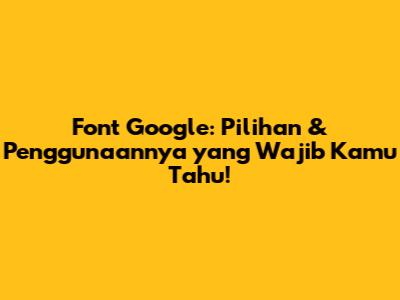
- Roboto: Roboto adalah font sans-serif yang sangat serbaguna dan mudah dibaca. Font ini sering digunakan untuk website dan aplikasi karena tampilannya yang bersih dan modern. Roboto memiliki banyak variasi gaya, sehingga cocok untuk berbagai kebutuhan desain.
- Open Sans: Open Sans adalah font sans-serif lainnya yang sangat populer. Font ini dirancang untuk tampilan di layar, sehingga sangat cocok untuk website. Open Sans juga mudah dibaca dan memiliki tampilan yang ramah.
- Lato: Lato adalah font sans-serif yang elegan dan modern. Font ini cocok untuk berbagai jenis proyek, termasuk website, logo, dan materi pemasaran. Lato memiliki bentuk yang unik dan mudah dikenali.
- Montserrat: Montserrat adalah font sans-serif yang terinspirasi oleh arsitektur kota Montserrat di Argentina. Font ini memiliki tampilan yang bersih dan geometris, sehingga cocok untuk desain yang modern dan minimalis.
- Poppins: Poppins adalah font sans-serif yang modern dan ramah. Font ini cocok untuk berbagai jenis proyek, termasuk website, aplikasi, dan materi pemasaran. Poppins memiliki bentuk yang bulat dan mudah dikenali.
- Raleway: Raleway adalah font sans-serif yang elegan dan bergaya. Font ini cocok untuk berbagai jenis proyek, termasuk website, logo, dan materi pemasaran. Raleway memiliki tampilan yang bersih dan modern.
- Pertimbangkan Tujuan Desain: Apa tujuan utama dari desain kamu? Apakah kamu ingin menciptakan tampilan yang formal, kasual, modern, atau klasik? Pilihlah font yang sesuai dengan tujuan desain kamu.
- Perhatikan Keterbacaan: Pastikan font yang kamu pilih mudah dibaca, terutama untuk teks dalam jumlah banyak. Hindari font yang terlalu rumit atau sulit dibaca.
- Periksa Kombinasi Font: Jika kamu menggunakan lebih dari satu font, pastikan font-font tersebut saling melengkapi dan tidak bertentangan satu sama lain. Kamu bisa menggunakan alat seperti Google Fonts Pairings untuk mendapatkan saran kombinasi font yang baik.
- Perhatikan Karakteristik Font: Perhatikan detail-detail seperti bentuk huruf, ketebalan, dan jarak antar huruf. Pastikan karakteristik font sesuai dengan gaya desain kamu.
- Uji Coba di Berbagai Perangkat: Pastikan font yang kamu pilih terlihat bagus di berbagai perangkat dan ukuran layar. Lakukan pengujian di komputer, tablet, dan smartphone.
- Gunakan Font yang Konsisten: Gunakan font yang konsisten di seluruh website atau proyek kamu. Ini akan membantu menciptakan tampilan yang profesional dan konsisten.
- Jangan Takut Bereksperimen: Cobalah berbagai font untuk menemukan yang paling cocok untuk proyek kamu. Jangan takut untuk bereksperimen dan mencoba hal-hal baru.
Font Google adalah salah satu sumber daya paling berharga bagi desainer web, desainer grafis, dan siapa pun yang tertarik dengan tipografi. Guys, kalian pasti sering banget kan lihat berbagai jenis tulisan di website atau aplikasi? Nah, sebagian besar dari tulisan-tulisan itu menggunakan font-font keren yang disediakan oleh Google. Artikel ini akan membahas secara mendalam tentang font yang digunakan oleh Google, mengapa mereka begitu populer, dan bagaimana kamu bisa memanfaatkannya untuk proyek-proyek kreatifmu. Jadi, mari kita selami dunia font Google!
Apa Itu Font Google?
Font Google atau Google Fonts adalah sebuah perpustakaan yang berisi ratusan jenis font yang bisa digunakan secara gratis. Yup, benar banget, GRATIS! Google Fonts menyediakan akses terbuka ke koleksi font yang sangat beragam, mulai dari font serif klasik hingga font sans-serif modern, bahkan hingga font display yang unik. Perpustakaan ini dikelola oleh Google dan terus diperbarui dengan font-font baru yang berkualitas tinggi. Tujuannya adalah untuk membuat tipografi yang baik dapat diakses oleh semua orang, tanpa batasan biaya. Bayangin aja, dulu untuk mendapatkan font yang bagus, kita harus merogoh kocek lumayan dalam. Tapi sekarang, dengan Google Fonts, semua jadi lebih mudah dan terjangkau.